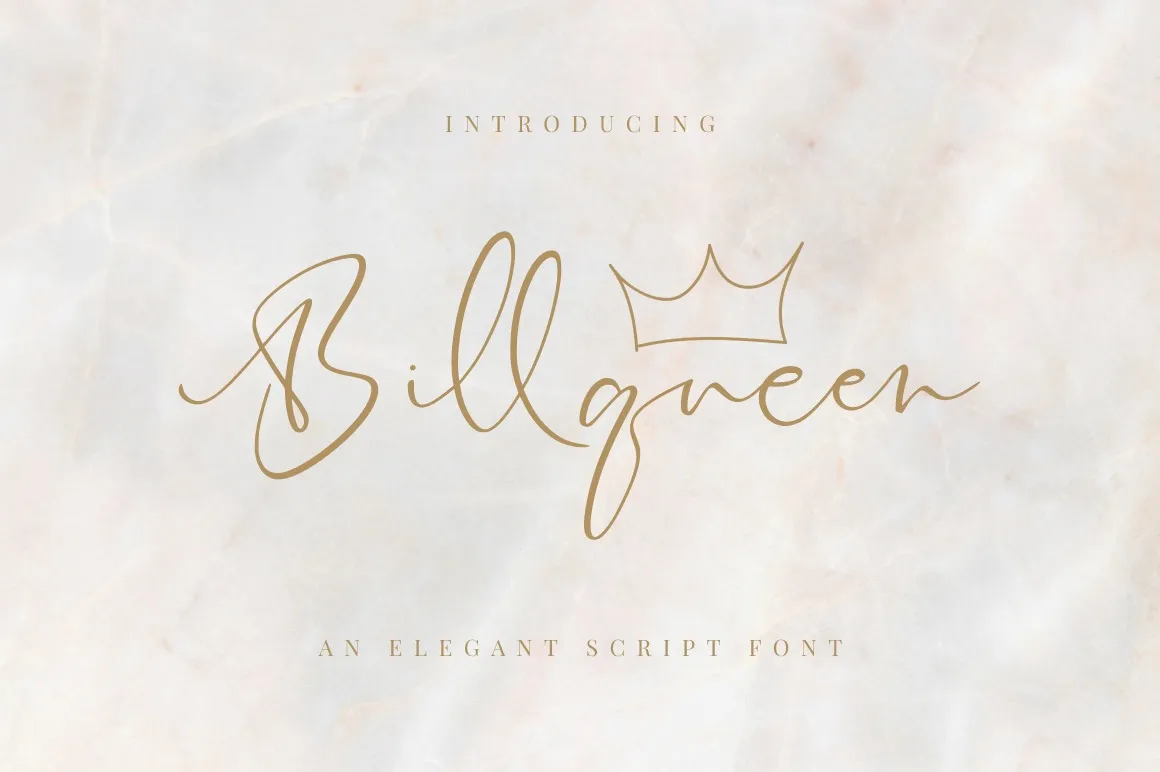
Esta fonte ‘Billqueen Font’ é uma elegante escolha para quem procura um estilo retrô sofisticado com um toque natural e relaxado. Desenvolvida pelo designer Tedyindrawan, a fonte apresenta linhas finas e levemente onduladas que dão ao texto um ar autêntico e contemporâneo. Suas formas curvas delicadas e seu charme natural fazem da ‘Billqueen Font’ uma opção perfeita para designers buscam uma combinação única de elegância e conforto, seja em design de logotipos ou ilustrações. Este script font é adequado tanto para um estilo retrô quanto para um visual mais moderno, tornando-o versátil e adaptável a uma ampla gama de projetos gráficos.